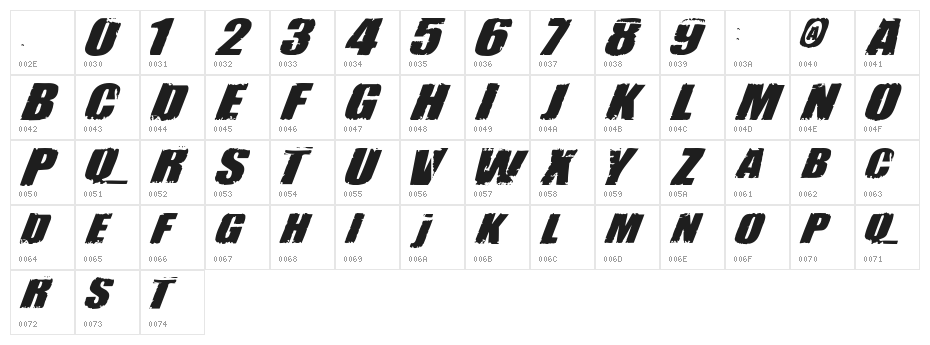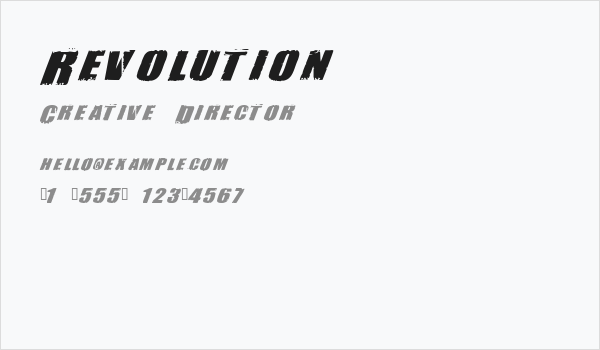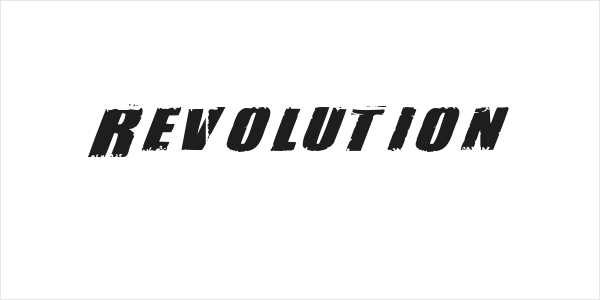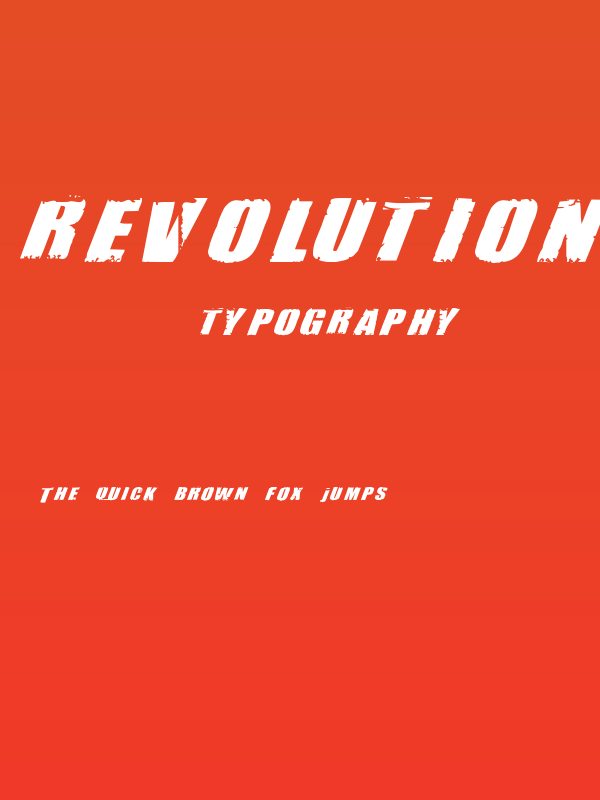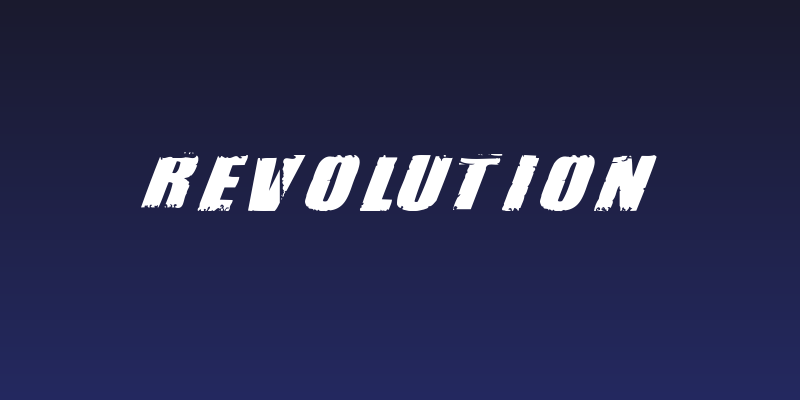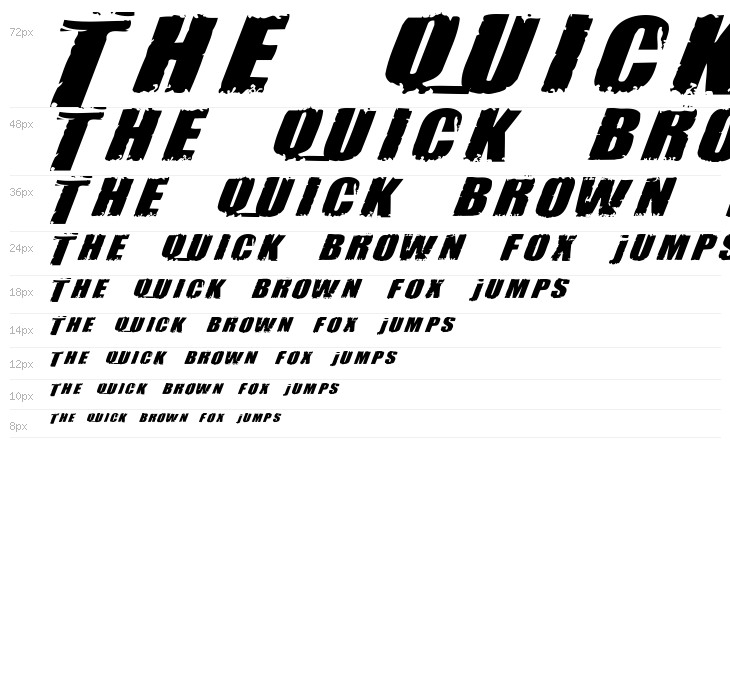
Revolution Font
✎ Distorted Eroded
| Categorii | Distorted Eroded |
| Stil general | Modern, Urban, Energetic |
| Caz de utilizare | Headlines, Posters, Branding |
| Proiecte propuse | Ideal for posters, branding, headlines, and any design needing a bold, gritty impact. |